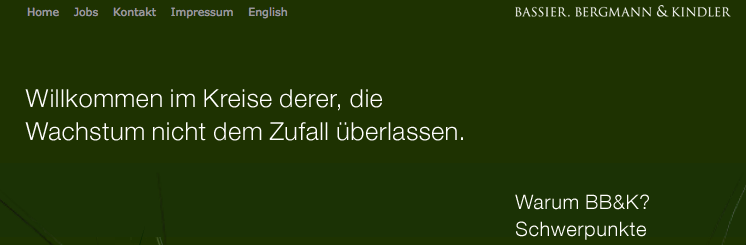
Hausschriften von BB&K - Bassier. Bergmann & Kindler?
erstmal das Font-Beispiel (alternativ einfach die BB&K-Website besuchen):
Welche beiden Fonts sind das? Die große in der Mitte sieht mir nach einer leichten Helvetica aus, oder? Und die oben rechts, die den Firmenschriftzug bildet?
Die verwenden als Textschrift
- HelveticaNeueBB-K-Light
- HelveticaNeueBB-K-Medium
trajan: